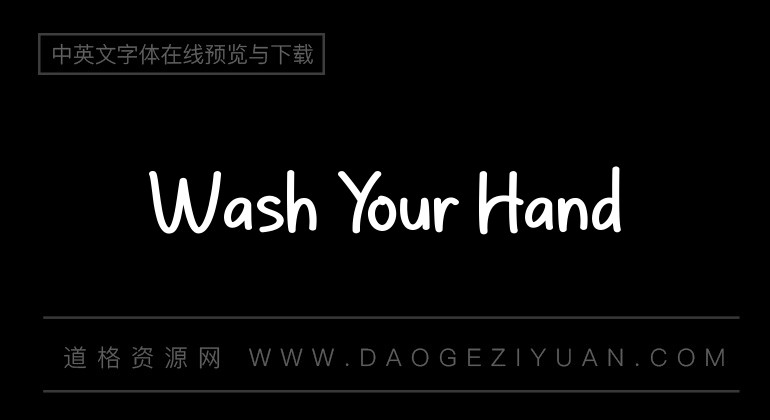
"Wash Your Hand" 字体是一种免费的手写字体,旨在提醒人们在COVID-19大流行期间保持卫生。它由设计师Monica和Marcelo创建,可以在Google Fonts上免费下载和使用。 该字体采用手写风格,字母有不规则的形状,字母之间的间距有些不对称,这使其看起来更加自然和真实。整个字体不仅具有现代感,而且显得有趣、友好和亲切。此外,"Wash Your Hand" 字体还提供了数种不同的版本和变体,以适应不同的设计需求。 该字体成为COVID-19疫情期间非常受欢迎,因为它可以轻松地传达关于洗手和保持卫生的重要信息,帮助人们更好地理解和遵守卫生规定。内容介绍
Wash Your Hand是一款非常不错的手写艺术字体,具有很好的视觉感,适合于文化类的宣传设计、商业类品牌的广告和产品包装设计以及个性化文字排版等较多场景。